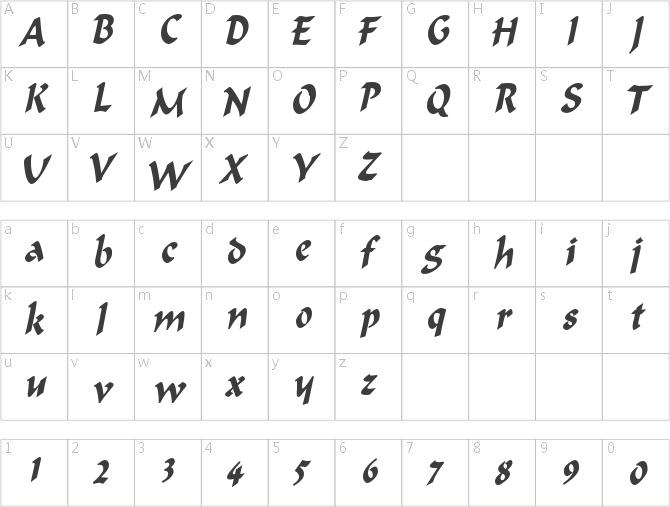
Marlin-Condensed-BoldItalic
Marlin-Condensed-BoldItalic介紹
Marlin-Condensed-BoldItalic字體字庫是一款讓人賞心悅目、百看不厭的英文字體,適合各類廣告和產品包裝設計應用,字體大小0.06MB,格式為ttf字體,上傳用戶是Elieen,作者/版權方為未知